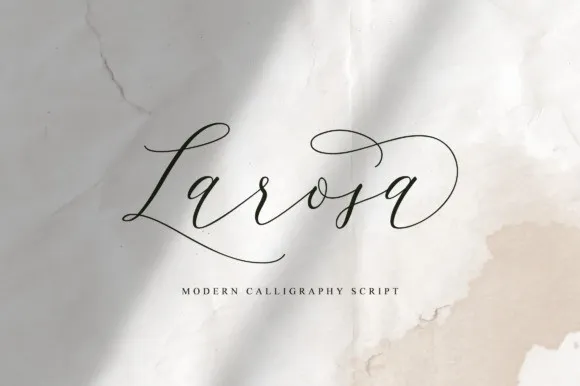
Larosa Script Font – Download Grátis
Lançamos uma nova fonte script chamada Larosa Font, que está repleta de elegância e luxo moderno. Esta fonte é perfeita para projetos criativos como a adição de marcas nas fotos, citações, capas de álbum, logomarcas, cartões de visita, entre outros projetos de design. Foi desenhada pela Letteratom e é uma escrita à mão que se destaca em logotipos, suprimentos para casamentos, marca, embalagens de beleza e muito mais. Utilize a Larosa Font para criar designs limpos e elegantes. Seja seu próximo projeto um marco importante na sua carreira!